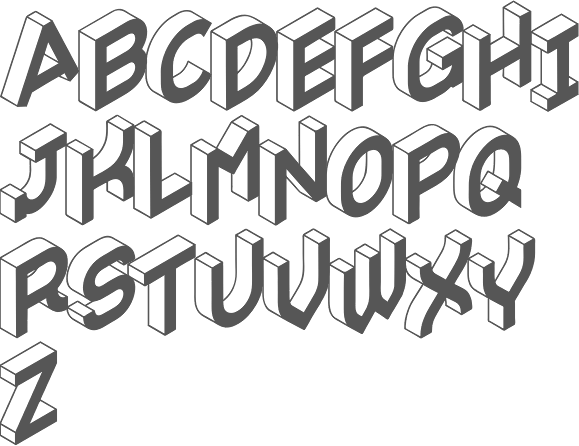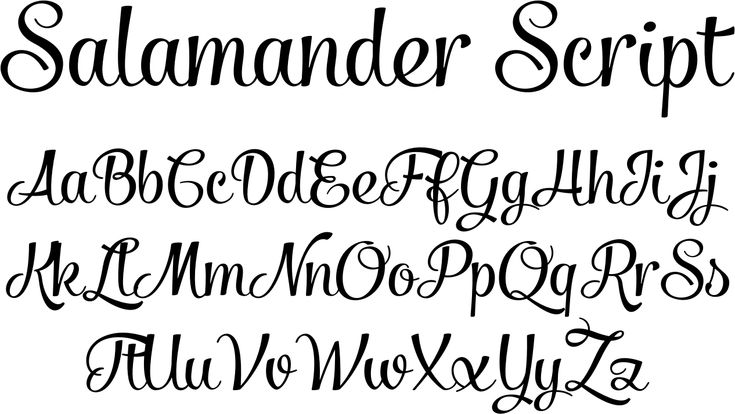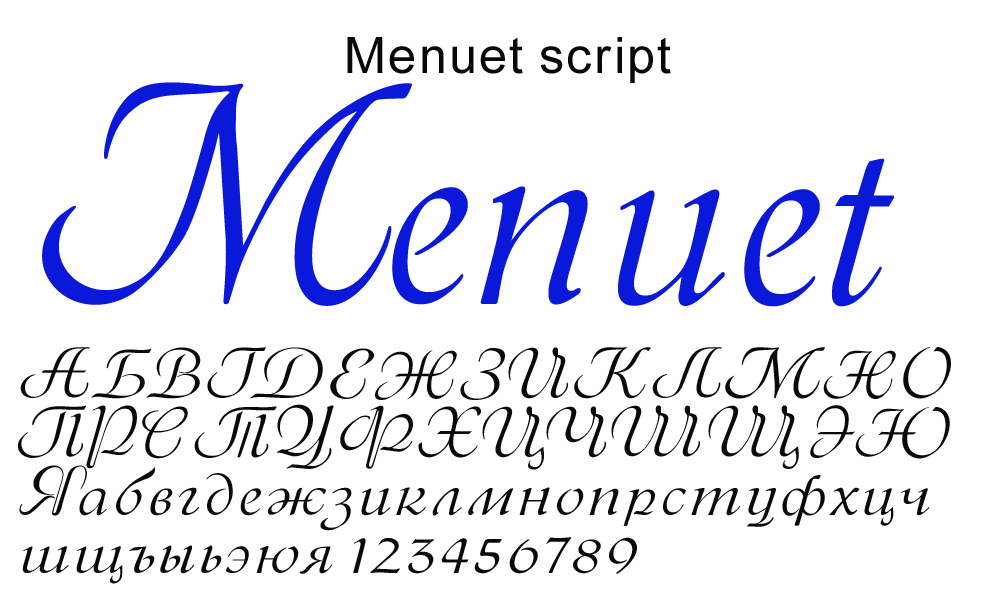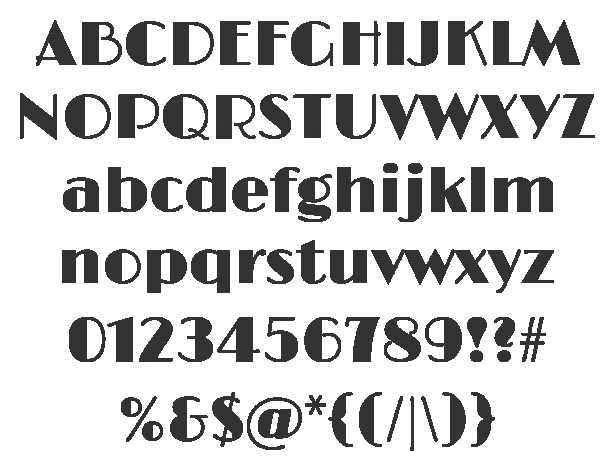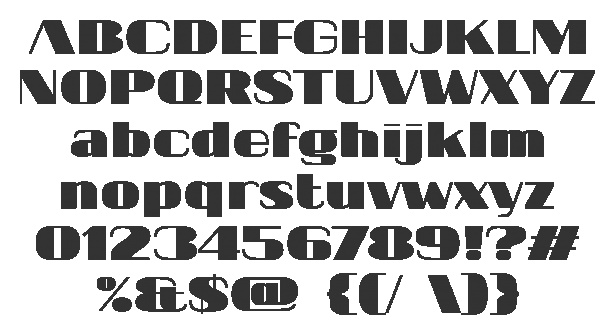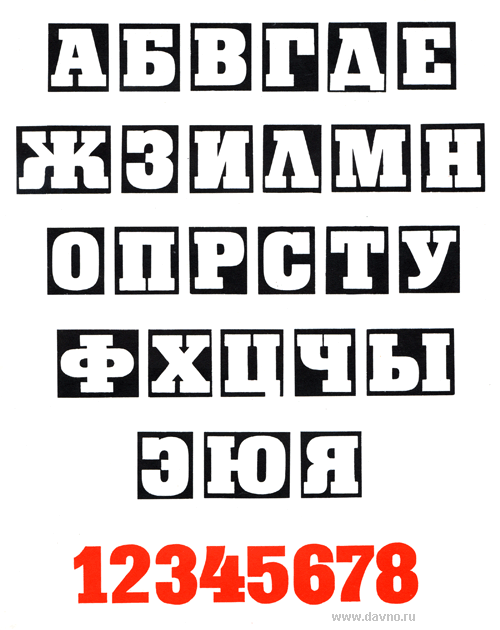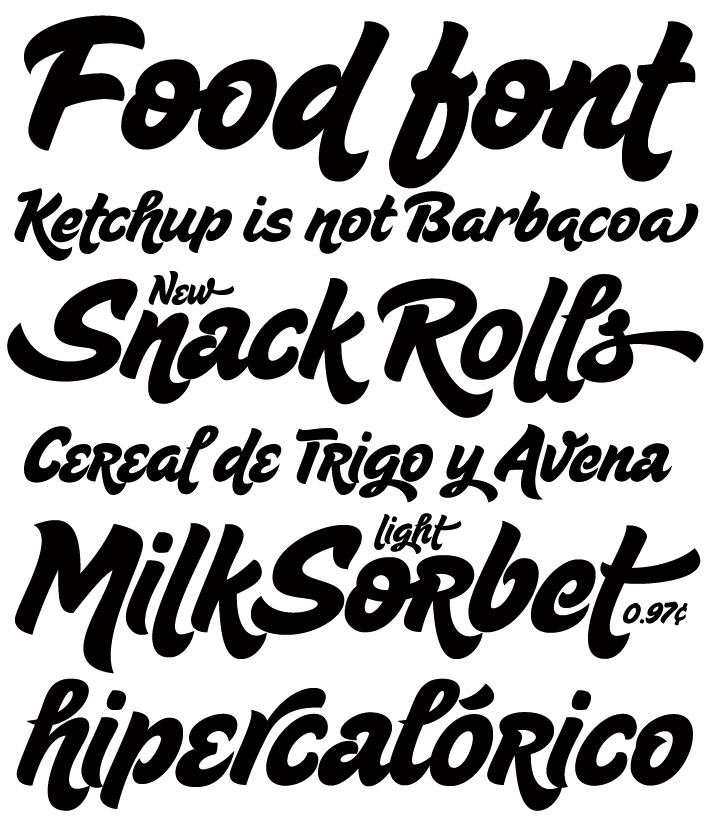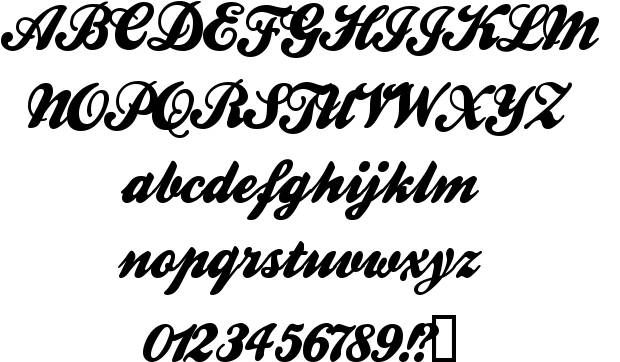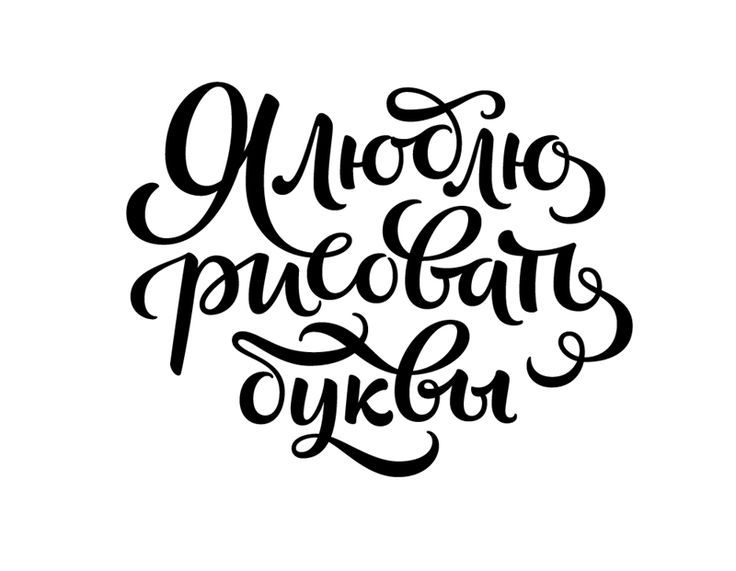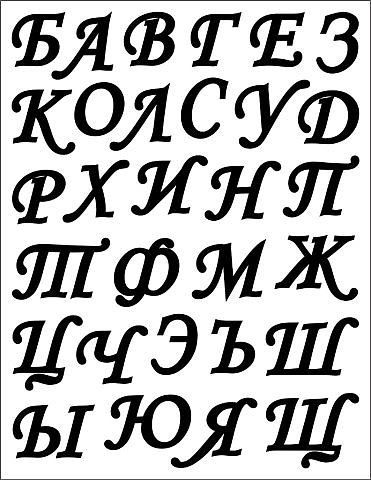
Как писать жирным и толстым шрифтом на youtube
Хотите, чтобы ваш канал выделялся на фоне других?
→ Один из способов это сделать — использовать нестандартные шрифты.
В этой статье мы выясним: ↓↓↓
- как писать жирным шрифтом на Youtube
- как писать курсивом и зачеркнутым шрифтом
- какие шрифты популярны среди ютуберов
Поехали !!!
- Как изменить шрифт в комментариях?
- Супер эффект- перевернутое начертание
- Для шапочки и preview на Youtube
- Итог
Как изменить шрифт в комментариях?
Есть две веские причины, по которым имеет смысл менять стиль начертания символов в комментариях: ↓↓↓
- Это выделит ваши ответы на комментарии подписчиков вашего канала
- Комментарии на Youtube со своим шрифтом помогут вам продвигать свой канал, выделяя их на фоне других
→ Youtube позволяет выполнить следующие операции: ⇓⇓⇓
- Сделать начертание жирным.
Для этого перед и после текста вставьте символ *: *Мой комментарий*. Вот так можно писать толстым шрифтом на Youtube. - Сделать его наклонным. Для этого перед и после текста вставьте подчеркивание: _Мой комментарий_.
- Сделать его зачеркнутым. Для этого перед и после текста вставьте дефис: —Мой комментарий-.
Эти символы нужно вставлять на этапе написания комментария. Результат вы увидите, когда опубликуете его.
Важно!
Между символами и текстом не должно быть пробела.
Супер эффект- перевернутое начертание
Кроме жирного, курсивного и подчеркнутого начертания шрифт в Youtube можно перевернуть с ног на голову.
→ Он повернется на 180 градусов.
При этом читать его нужно будет справа налево. Выглядит это очень эффектно, и не обратить внимание на такой комментария просто невозможно. ↓↓↓
Как это сделать ?
Работает он следующим образом. Вы вставляете исходный текст, каждый символ в котором заменяется символов Юникода.
Получается перевернутый текст, который можно скопировать и использовать где угодно — в том числе, на Ютубе.
Как пользоваться сервисом?
Для шапочки и preview на Youtube
Оформление шапки и превью играет важную роль в продвижении канала.
Поэтому каждый ютубер стремится сделать их максимально привлекательными !!!
• Шапка — это баннер вверху страницы вашего канала с его названием и другой информацией.
• Превью — это картинка, кадр перед началом ролика.
Ютуб позволяет задавать их для каждого вашего видео.
Это намного эффективнее, чем случайный кадр, который может ни о чем не говорить зрителю.
Шапки и превью можно создавать с помощью Photoshop или другого графического редактора. В этом случае к вашим услугам вся их мощь. В интернете также можно найти и скачать готовые шаблоны превью и шапок. Вам нужно будет только подставить в них свой текст.
Особое внимание нужно обратить на то — какие шрифты для канала Youtube вы используете. Отталкивайтесь от его тематики.
• К примеру, те, которые популярны среди летсплейщиков, могут не подойти для образовательного или посвященного бизнесу аккаунта.
Среди популярных нельзя не отметить такие красивые шрифты для шапки Youtube: ↓↓↓
- ObelixPro
- BadaBoomBB
- BIPs
- BancoDi
На самом деле, список намного больше….
Итог
• Вы узнали о том, как сделать жирный шрифт в Youtube, а также курсивным и перечеркнутым.
• Мы также обсудили вопрос создания шапки и превью и использования популярных шрифтов для этого.
Используйте эти знания, чтобы придать индивидуальности вашему каналу и продвигать его!
Как поменять шрифт в WhatsApp?
Знали ли вы, что в ватсап можно поменять шрифт ваших сообщений? Эту функцию добавили в одном из обновлений, но для тех, кто использует мессенджер на старых платформах и не имеет возможности обновиться, такая возможность тоже имеется, хоть и немного по-другому.
Итак, как поменять шрифт в WhatsApp на жирный, курсив или зачеркнутый:
- Откройте мессенджер и любую переписку.
- Напишите нужный текст.
- Нажмите на него и удерживайте.
- В открывшемся меню выберите нужный вам шрифт.
Инструкция для Iphone и Android
53. Airone Font (бесплатно)
54. Onek Hokot (БЕСПЛАТНО)
Вдохновленные стилем «пузырькового» граффити и современной эстетикой 2000 года, Pixel Surplus и Onek Studio объединили таланты, чтобы предоставить вам этот удивительный жирный шрифт.